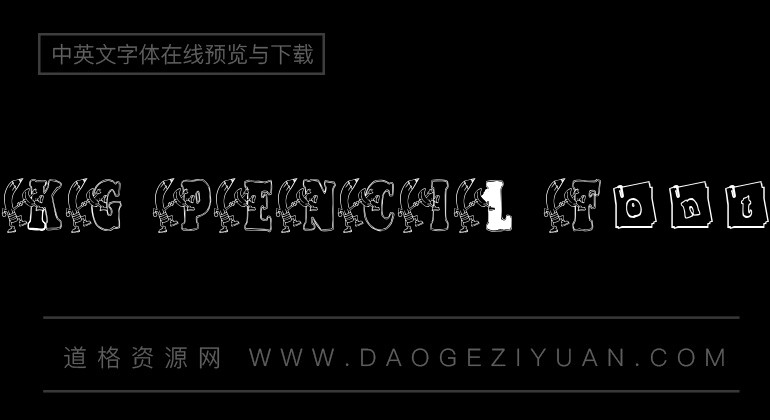
KG PENCIL Font
KG PENCIL是一种手写风格的字体,它有一种类似于铅笔书写的感觉。该字体由设计师Kimberly Geswein制作,她是一位独立的字体设计师,专注于创造美丽、有趣、易于使用的字体。KG PENCIL字体是她为数不多的手写字体之一,它非常适合用于儿童教育、手工制作、贺卡、海报等设计项目。该字体在许多设计社区和网站上都非常受欢迎,因为它使设计师可以轻松地创建出有趣、可爱的项目。
KG PENCIL Font是一款非常不错的手写艺术字体,具有很好的视觉感,适合于文化类的宣传设计、商业类品牌的广告和产品包装设计以及个性化文字排版等较多场景。